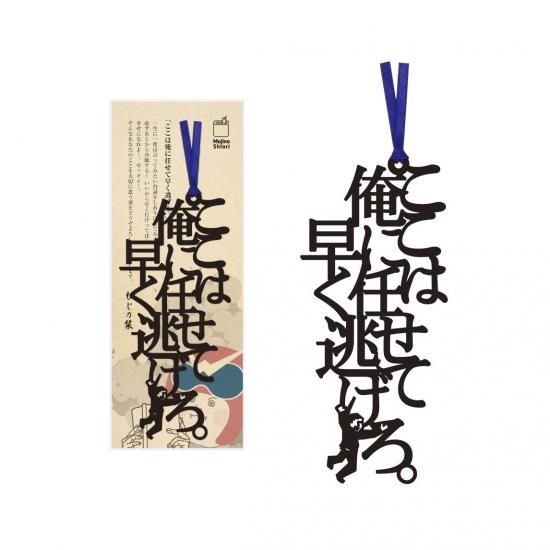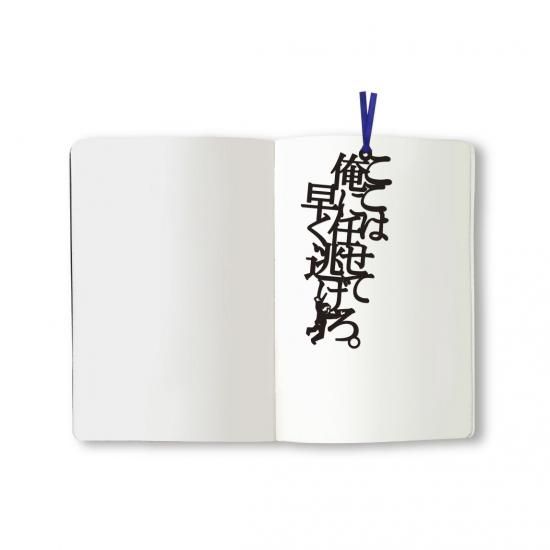
文字のしおり「ここは俺に任せて早く逃げろ。」
一生に一度は言ってみたい台詞をしおりにしてみました。
「ここは俺に任せて早く逃げろ。」
自己満足や自己陶酔と言わないで。
俺にかまわず逃げてくれ!必ずあとから合流する!いいから早く行けってば!
幸せになれよ・・・。ゼッタイ・・・。
そんなあなたのことを大切に思う栞をどうぞよろしくお願いします。
木材パルプや綿を原料とした環境素材を採用し、耐久性・耐水性に優れたファイバーの特徴を活かすことで、言葉がフォントごと切り取られたような巧緻で美しい『文字のしおり』のデザインが実現しています。